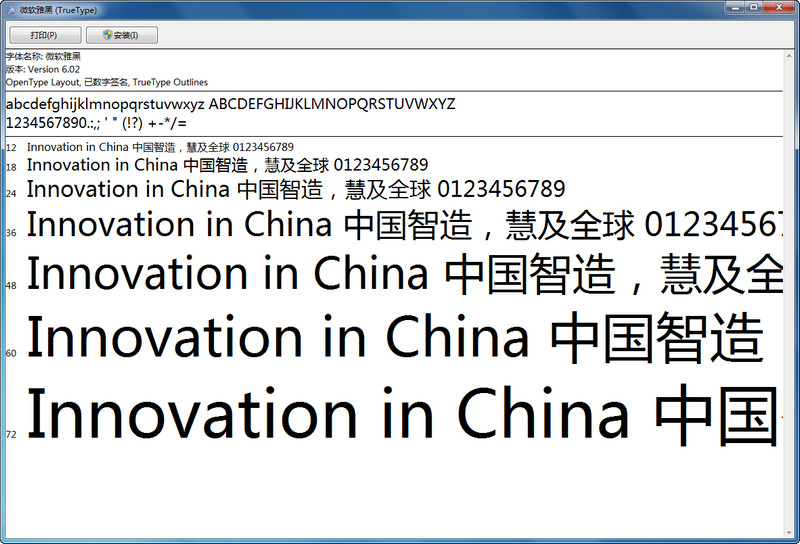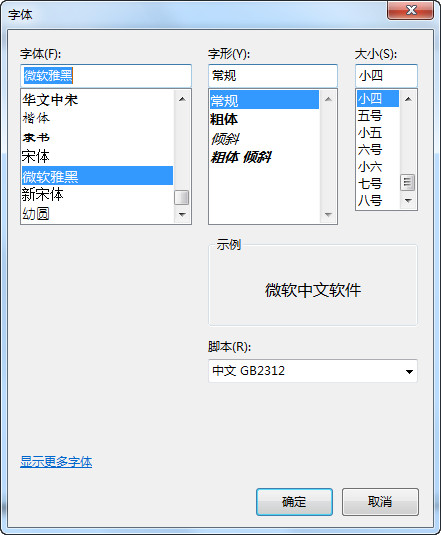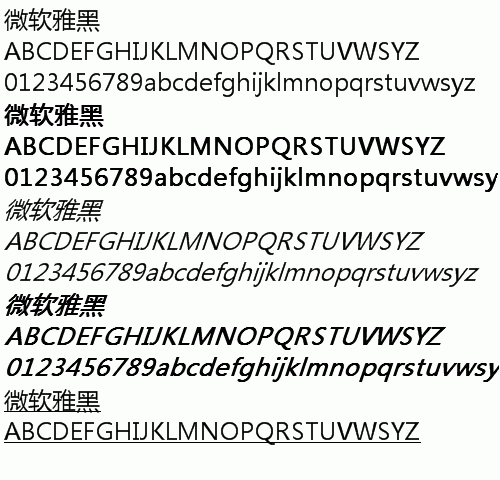
微軟雅黑ttf是美國微軟公司委托中國北大方正電子有限公司設計的一款全面支持ClearType技術的字體。Monotype公司負責字體Hinting工作。它屬于OpenType類型,文件名是MSYH.TTF,字體設計上屬于無襯線字體和黑體。這種字體每個字的造價成本在100美元左右。該字體家族還包括“微軟雅黑Bold”(粗體),文件名為MSYHBD.TTF。這個粗體不是單純的將普通字符加粗,而是在具體筆畫上分別進行處理,因此是獨立的一個字體。微軟雅黑隨簡體中文版Windows Vista一起發(fā)布,是Windows Vista默認字體。另外,Microsoft office 2007簡體中文版也附帶這個字體。
在涵蓋的字庫上,微軟雅黑支持GBK字符集,包含了Unicode的所有 20902個中文字符以及中國國家標準化組織添加的大約 80個中文字符,還包含了Big5的繁體中文字符和GB2312中的簡體中文字符。
微軟雅黑體是一款全新的支持 ClearType技術的中文界面顯示字體浮出水面,這就是微軟雅黑體。
這款字體是一種全新的無襯線黑體,它的字形略呈扁方而飽滿,筆畫簡潔而舒展,易于閱讀。這款字體在 ClearType 技術下的清新和優(yōu)美著實給人留下了深刻的印象。同時,微軟方面也為這種新型字體付出了昂貴的代價?!斑@種字體每個字的造價成本在100美元左右,據(jù)不完全統(tǒng)計,我國各字典、詞海收錄有2萬多個漢字”。
1. 單獨設計的粗體。
2. 顯示品質優(yōu)異的斜體。
3. 更清晰的小號字顯示。
4. 對于最常用的字號。
5. 更優(yōu)美而現(xiàn)代的字形設計。